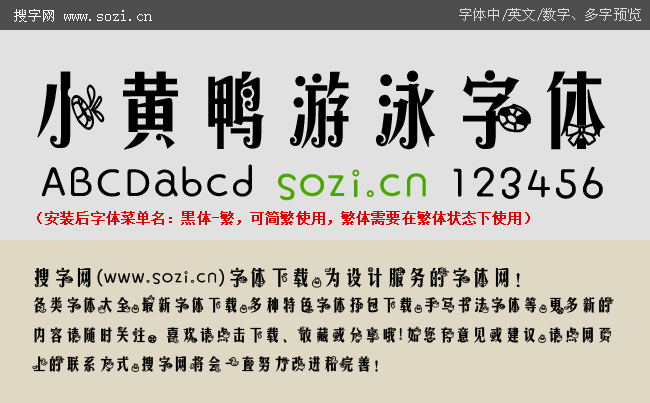
小黃鴨游泳字體
搜字網(wǎng)給大家提供一款小黃鴨游泳字體手機(jī)中文字體下載。這款手機(jī)字體是在長(zhǎng)藝體筆畫(huà)間插入了一些卡通圖案。長(zhǎng)藝體筆畫(huà)既有黑體的粗壯醒目,又有宋體的秀美柔和,加上藝術(shù)性的圓球形點(diǎn)、起筆如蝌蚪形的頓點(diǎn)、螺螄轉(zhuǎn)似的小鉤,配以修長(zhǎng)的字形,美觀而不落俗套。加入了卡通圖案后又增添了趣味性,特別適合喜歡手機(jī)字體個(gè)性一些的朋友在手機(jī)上安裝使用。